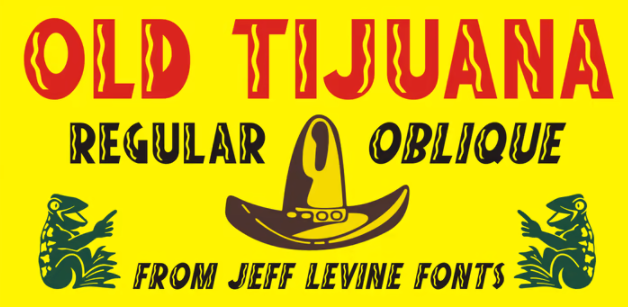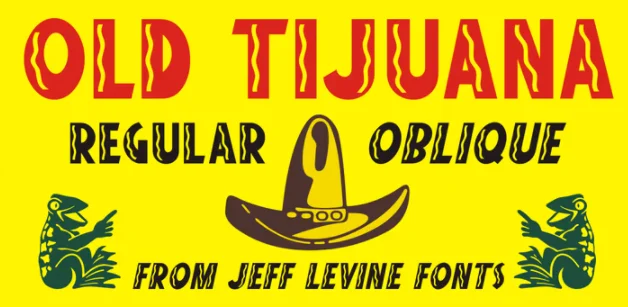
Шрифт Old Tijuana JNL был создан по образцу надписи от руки на обложке нотного альбома 1939 года "Class Will Tell" и доступен в обычной и наклонной версиях.
Непринужденный, игривый и напоминающий стиль "серапе" псевдомексиканских надписей, встречающихся в рекламных плакатах 1930-х и 1940-х годов, этот шрифт подходит не только для тематики южной границы.
Используйте его для любого праздничного случая, и дизайн хорошо впишется в интерьер.